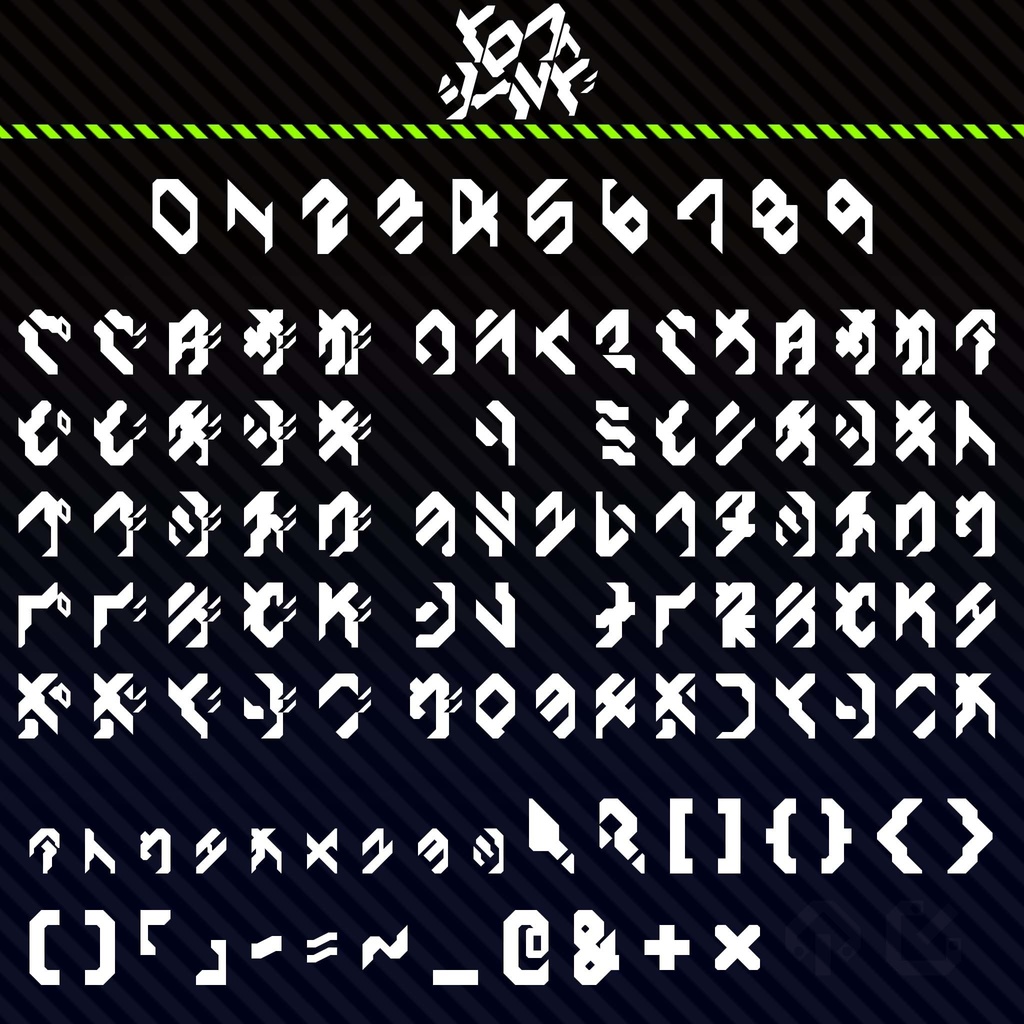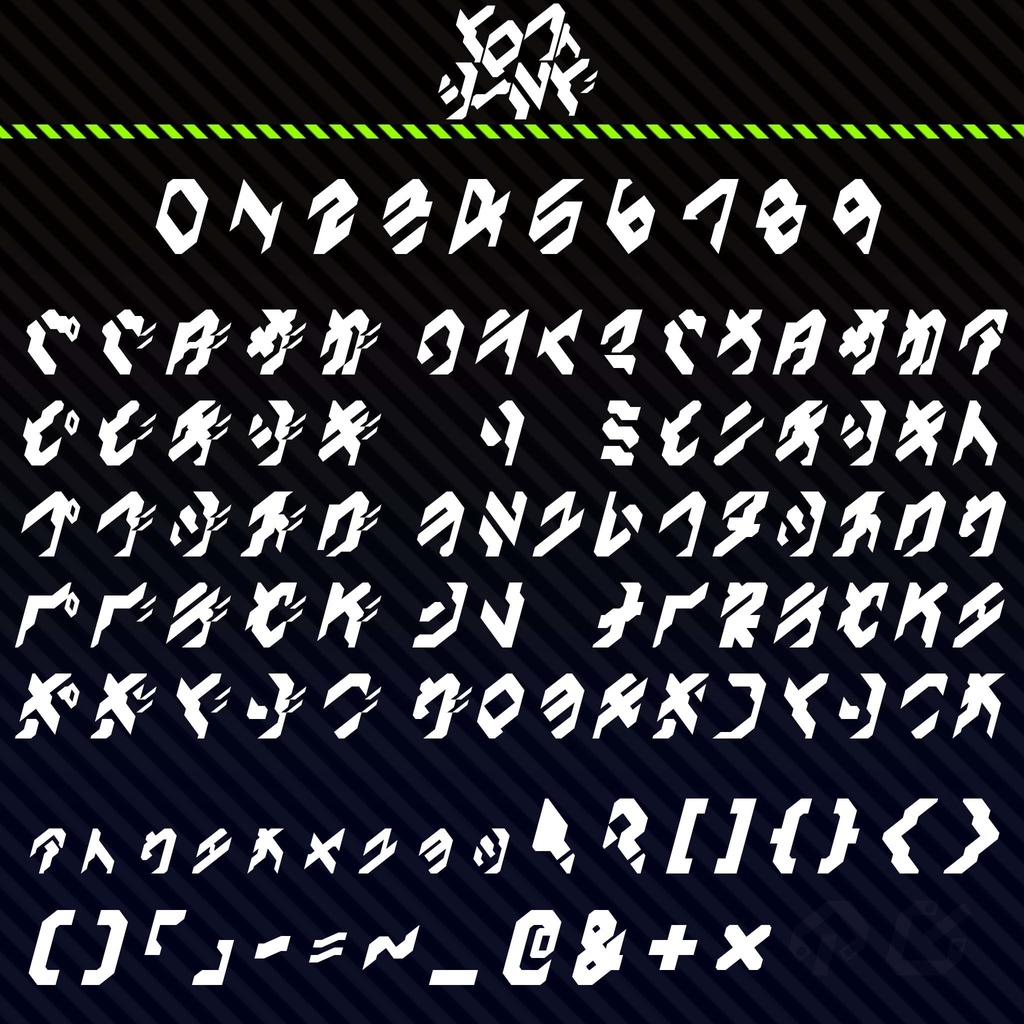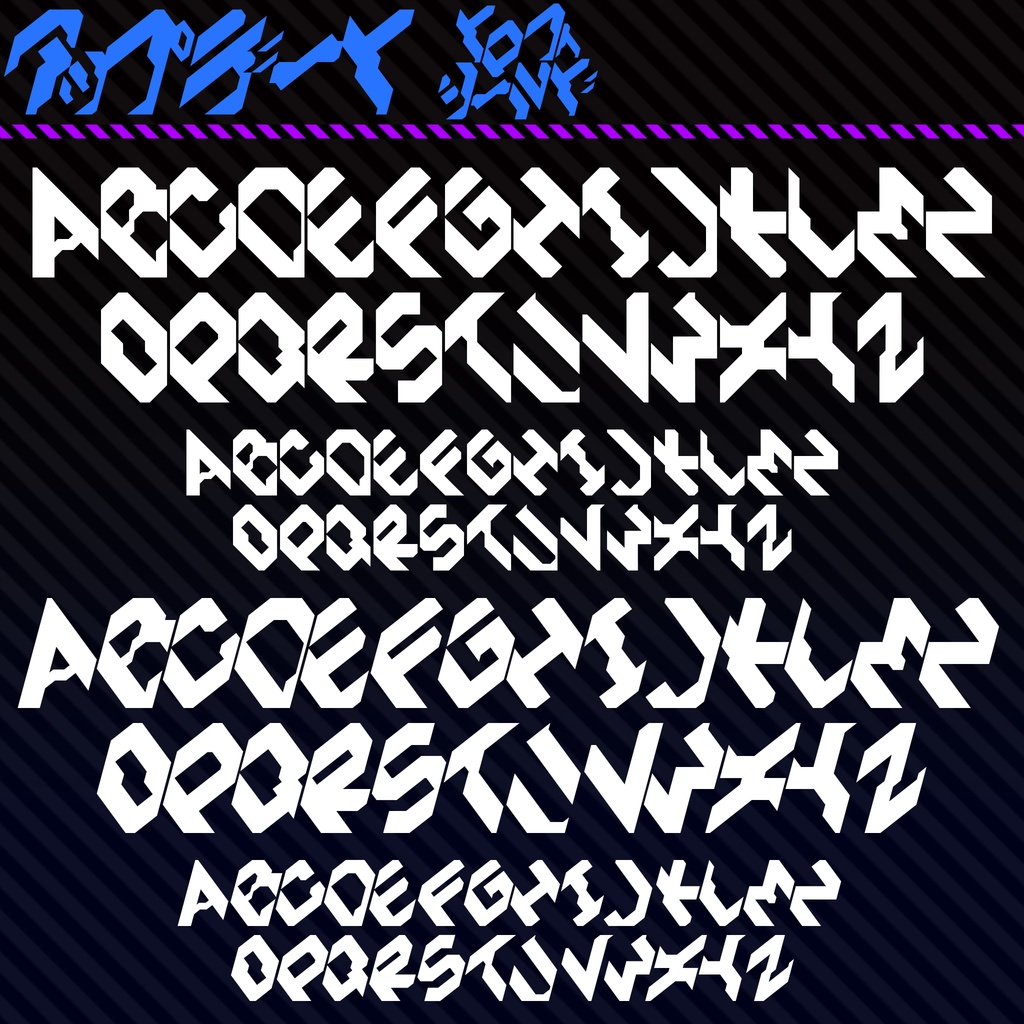
【配布】トロフィシールド【フォント】
VRChatのワールド用に作った文字をフォントとして纏めました。 SF作品向けの「カタカナ」フォントです。 とても読みづらく、長文を記すのに全く適していませんが、ろくでもない事を書いた時ばかりスラスラ読まれるので注意。 通常版に加えイタリック版(斜体)フォントも入っています。必要に応じてインストールしてください。 作者のスキルが足りないため、フォントのファミリー設定は出来ませんでした。
220123更新 ビが2つあったので差し替えました 220919更新 英語アルファベットを追加しました